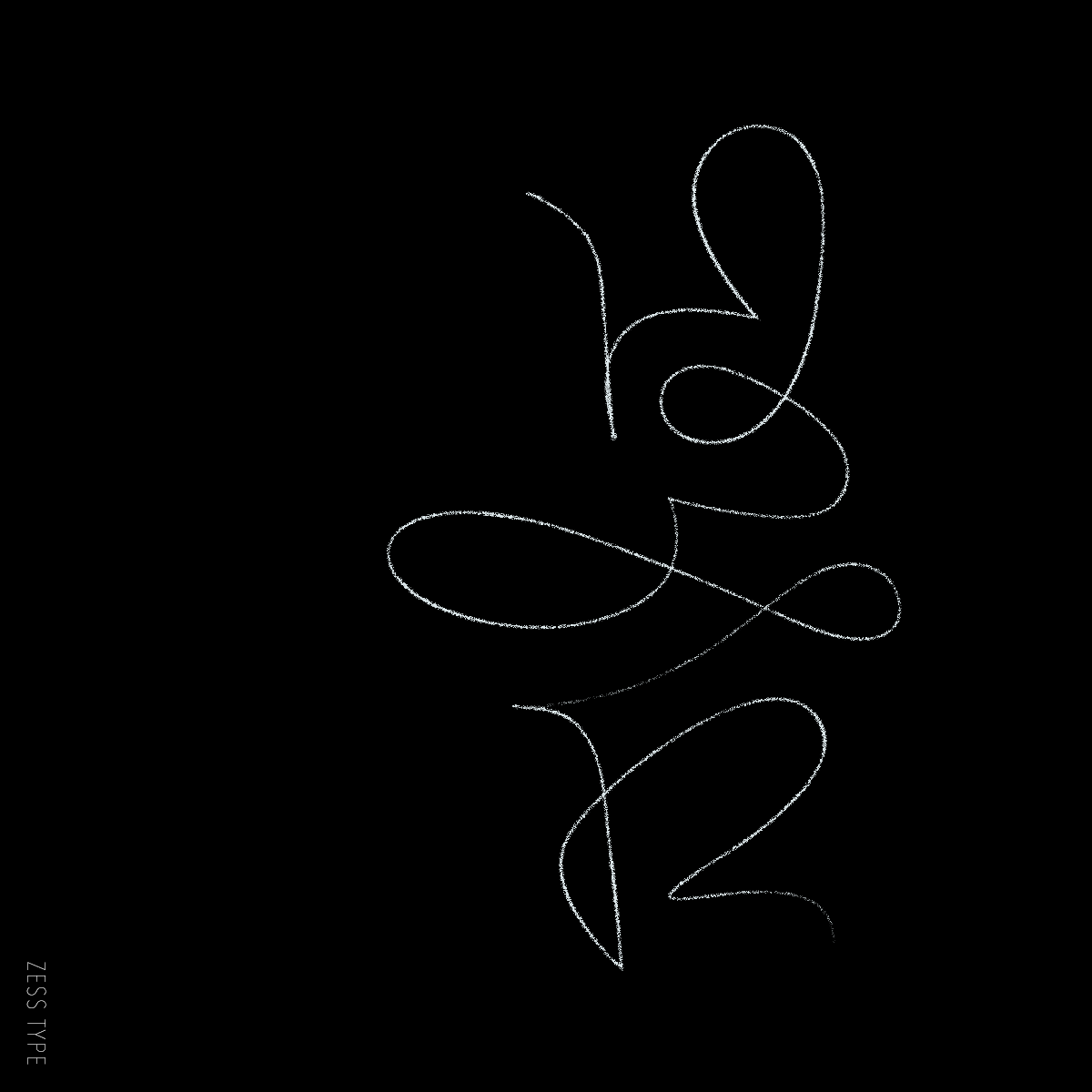
봄
ZESSTYPE LETTERING WORK 2017
글자표현탐구 소모임 <티테이블>의 봄맞이 프로젝트 <개화>를 앞두고 봄을 그리고 있습니다.
아직은 커브를 다루는게 서툴러서 수십번을 만져가며 패스와 씨름하곤 하지요.
이런 레터링 작업으로 커브 다루는 연습을 합니다.
지금은 직선적인 디자인의 고딕체와 그래픽적인 폰트들을 작업하고 있지만.
머지않아 커브가 익숙해지면 명조체나 더욱 다양한 폰트를 제작할 수 있겠지요.
그게 언제가 될지는 모르겠지만. 희망사항입니다.
그 희망을 이루기 위해서 꾸준히 작업하고 있구요.
추운 겨울날 봄을 맞을 준비를 하면서 이렇게 한글자 한글자 그리고 있으면.
그러한 희망에 한걸음 한걸음 다가가는 것 같아서 괜히 뿌듯하곤 합니다.
화이팅해야지요. 아직은 멀고 멀지만요.